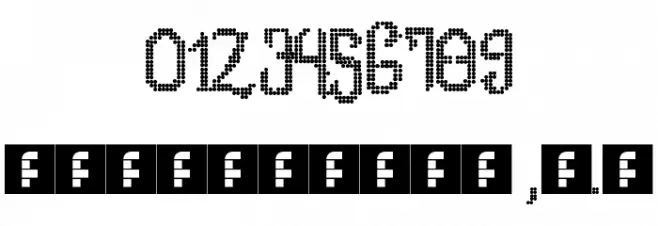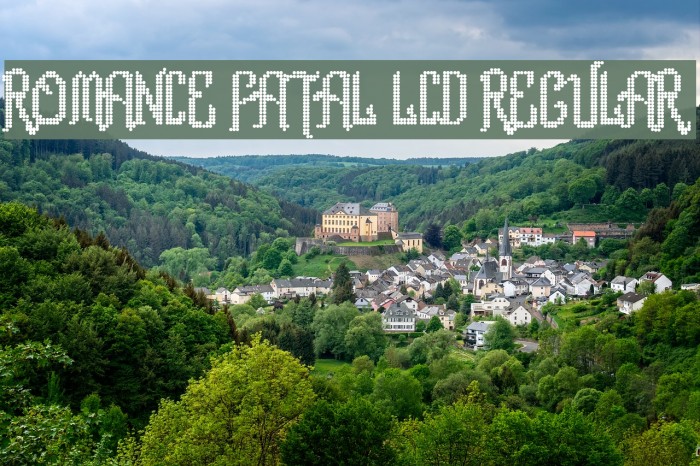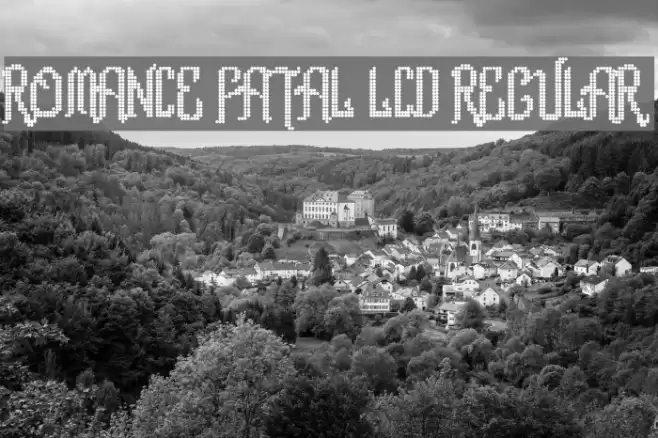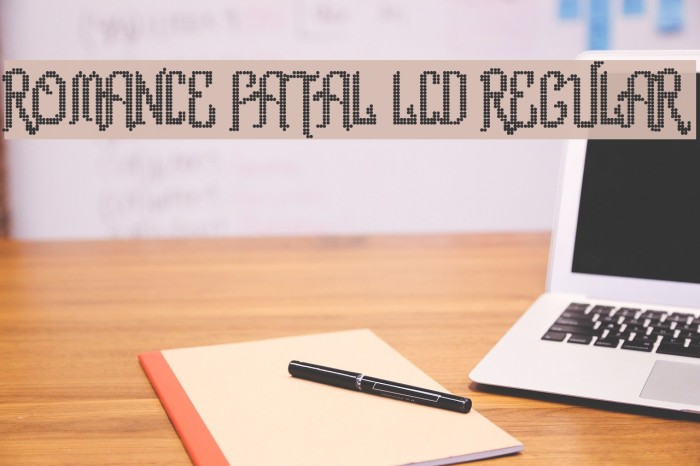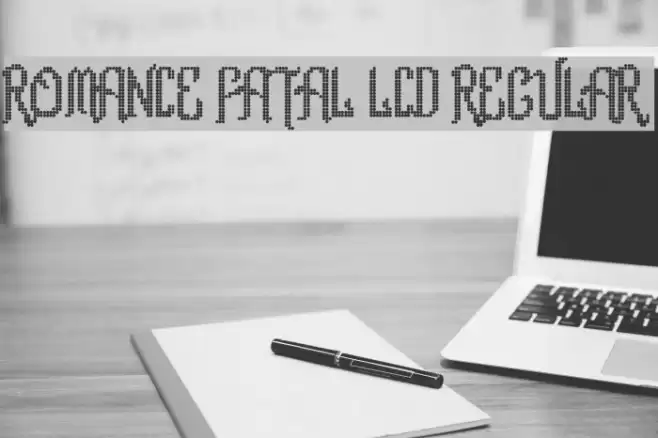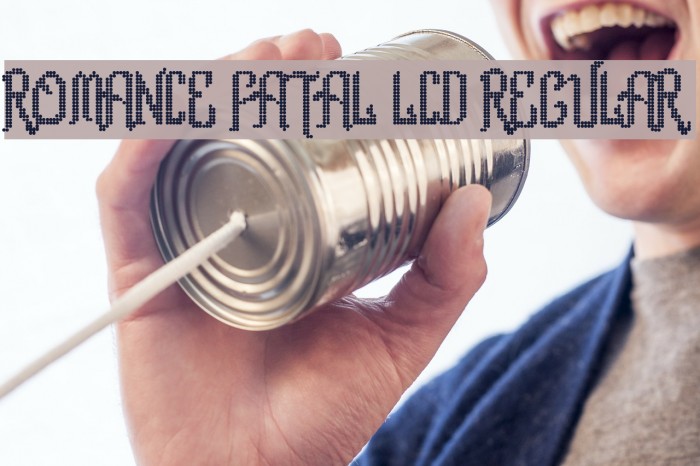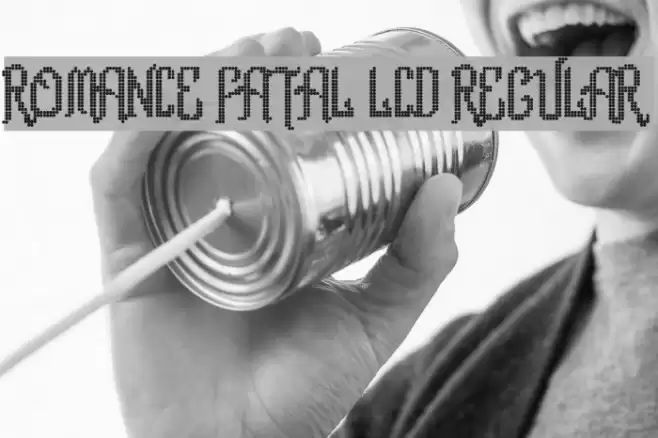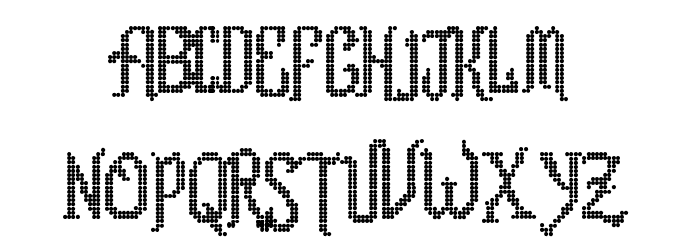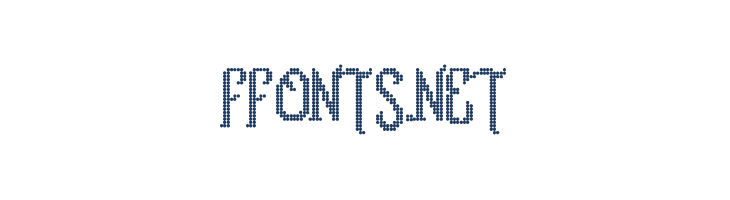
Romance fatal LCD Regular Font
Fonts by Juan Casco - www.juancasco.net
| 全体的なスタイル | Retro, Digital |
| 用途 | Logos, Posters, Digital Art |
| おすすめプロジェクト | Ideal for retro video game graphics, digital art projects, tech-themed posters, and nostalgic branding materials. |